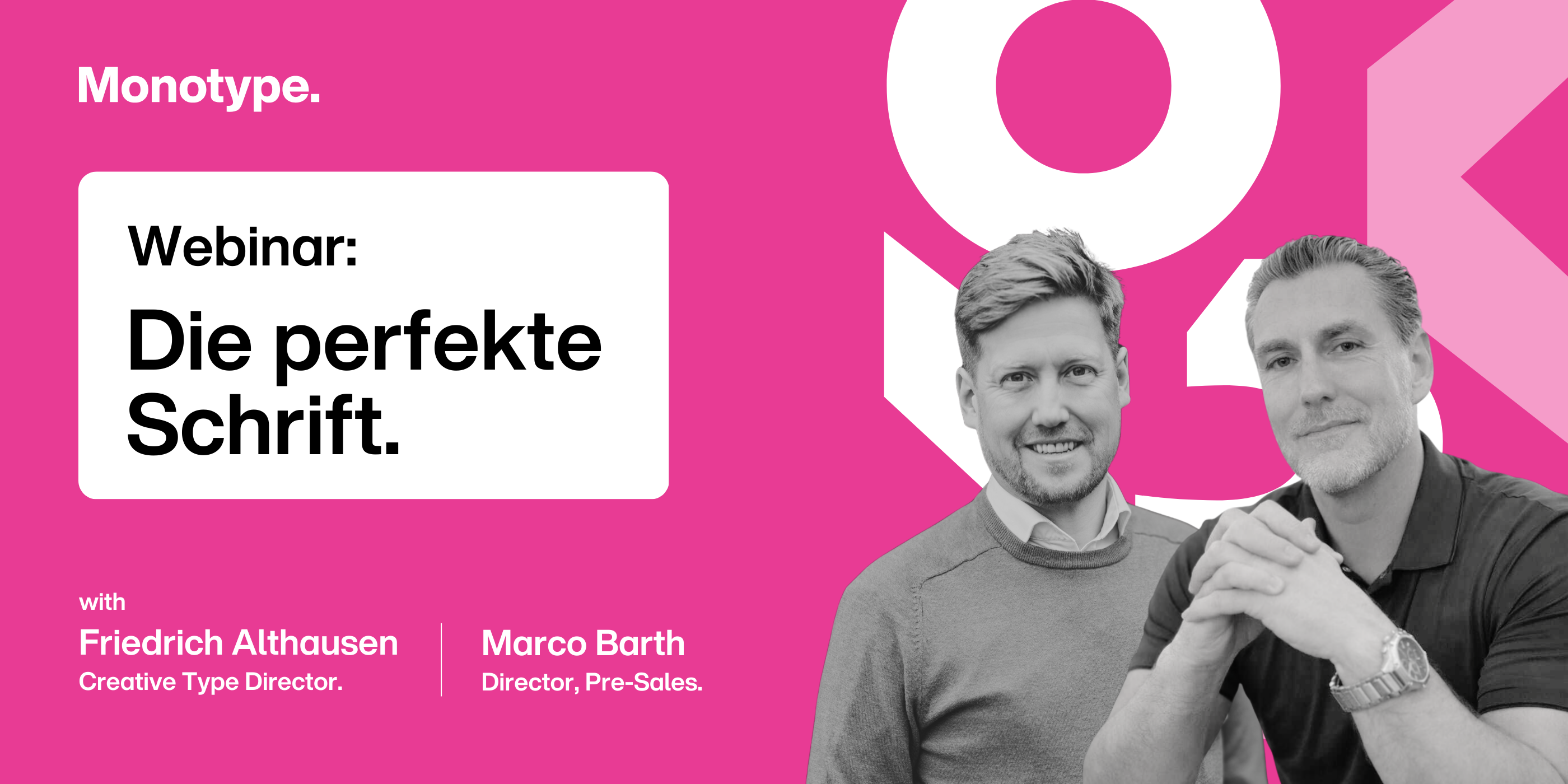
Die perfekte Schrift.
In einer Welt voller Marken entscheidet oft ein Detail über Wiedererkennung – die Typografie. Die richtige Schrift verleiht Ihrer Marke Charakter, Haltung und eine klare Stimme. Denken Sie an Disney, Netflix oder Siemens: Ein Buchstabe genügt, um die Marke zu erkennen.
Doch wie findet man bei Tausenden von Schriftarten die richtige?
In unserem kostenlosen Webinar am 25. Februar 2026 zeigen wir Ihnen, wie Sie mit Monotype Fonts schnell und sicher die passende Schrift für Ihre Marke auswählen.